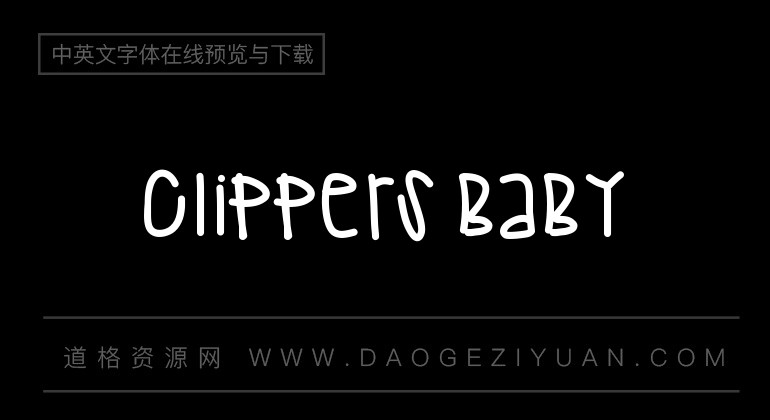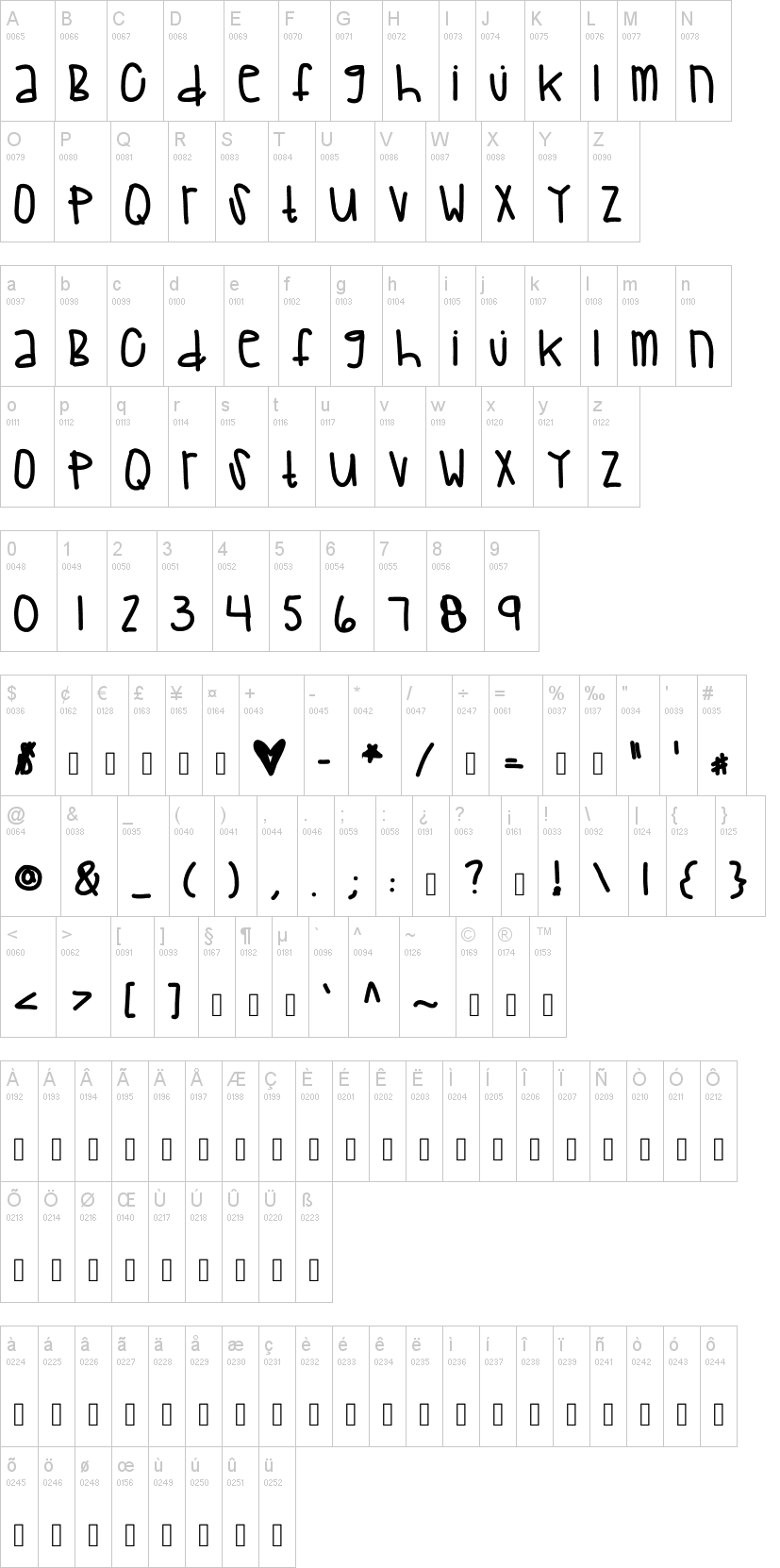
Clippers Baby
Clippers Baby是一种手写风格的字体,经常用于体育或娱乐品牌的标志和设计中。它的特点是线条比较粗,有些潦草的感觉,字母之间的距离也比较紧凑,给人一种活泼、轻松的感觉。这种字体常常用于象征年轻、有活力的品牌形象,尤其是在篮球领域中,Clippers Baby字体在洛杉矶快船队的标志中被广泛使用。
Clippers Baby是一款非常不错的手写艺术字体,具有很好的视觉感,适合于文化类的宣传设计、商业类品牌的广告和产品包装设计以及个性化文字排版等较多场景。